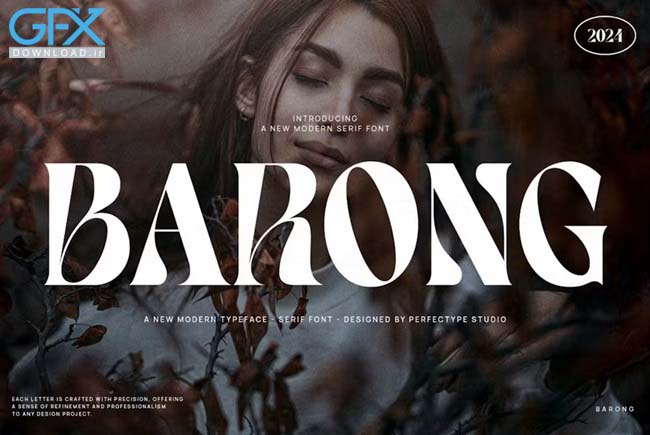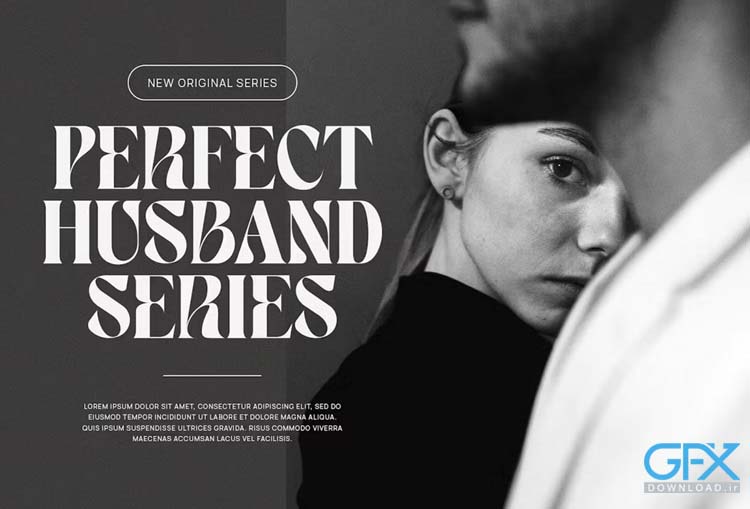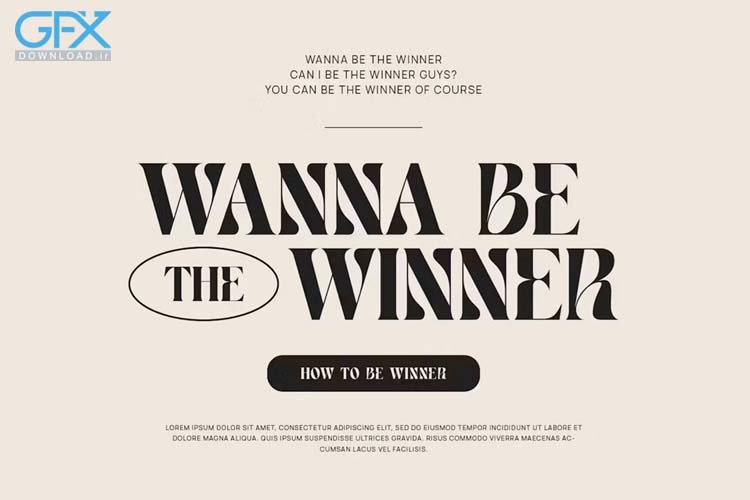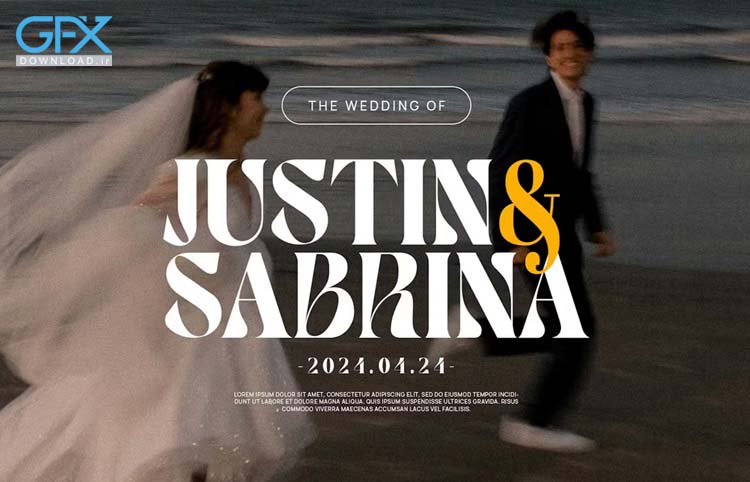
دانلود رایگان فونت انگلیسی شیک و جذاب Barong
دانلود فونت انگلیسی شیک و جذاب Barong به صورت کاملا رایگان در جی اف ایکس دانلود. شما می توانید از این فونت انگلیسی برای طراحی لوگو، برند سازی، پست های اینستاگرام، تبلیغات، برچسب ها، بسته بندی محصولات، عکاسی، طرح های عروسی، واترمارک، دعوت نامه و سایر موضوعات دیگر استفاده نمایید. در ادامه می توانید پیش نمایش را مشاهده و فایل اصلی فونت انگلیسی را به صورت کاملا رایگان از سایت دریافت نمایید.
طراحی توسط فونت انگلیسی رایگان barong
فونت انگلیسی رایگان barong برای عروسی
نمونه کاراکتر های فونت انگلیسی رایگان barong